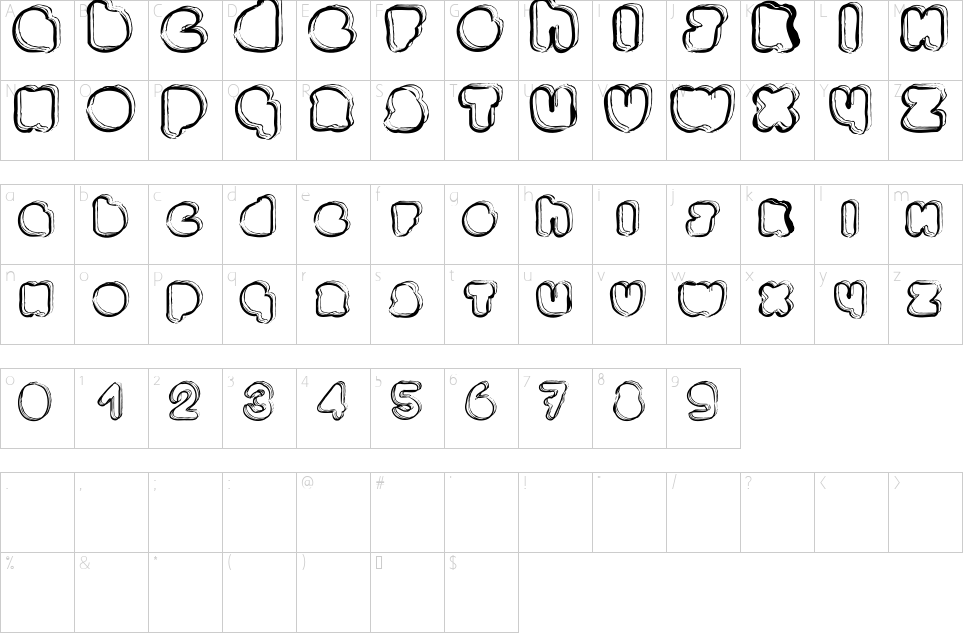
A fonte Ponctuation é uma opção gratuita e versátil para quem procura uma fonte para uso em projetos digitais. Ela foi projetada pela designer Maelle Keita e já foi baixada 2,090 vezes. Essa fonte é perfeita para aqueles que precisam de uma fonte de pontuação robusta e elegante. Através de seu design cuidadoso e funcional, a fonte Ponctuation adiciona um toque refinado a qualquer layout ou documento. É uma fonte gratuita, adequada para uso pessoal e comercial, e ideal para designers e criativos que valorizam as fontes de pontuação de alta qualidade. Descubra por si mesmo a diferença que essa fonte faz em seus projetos!